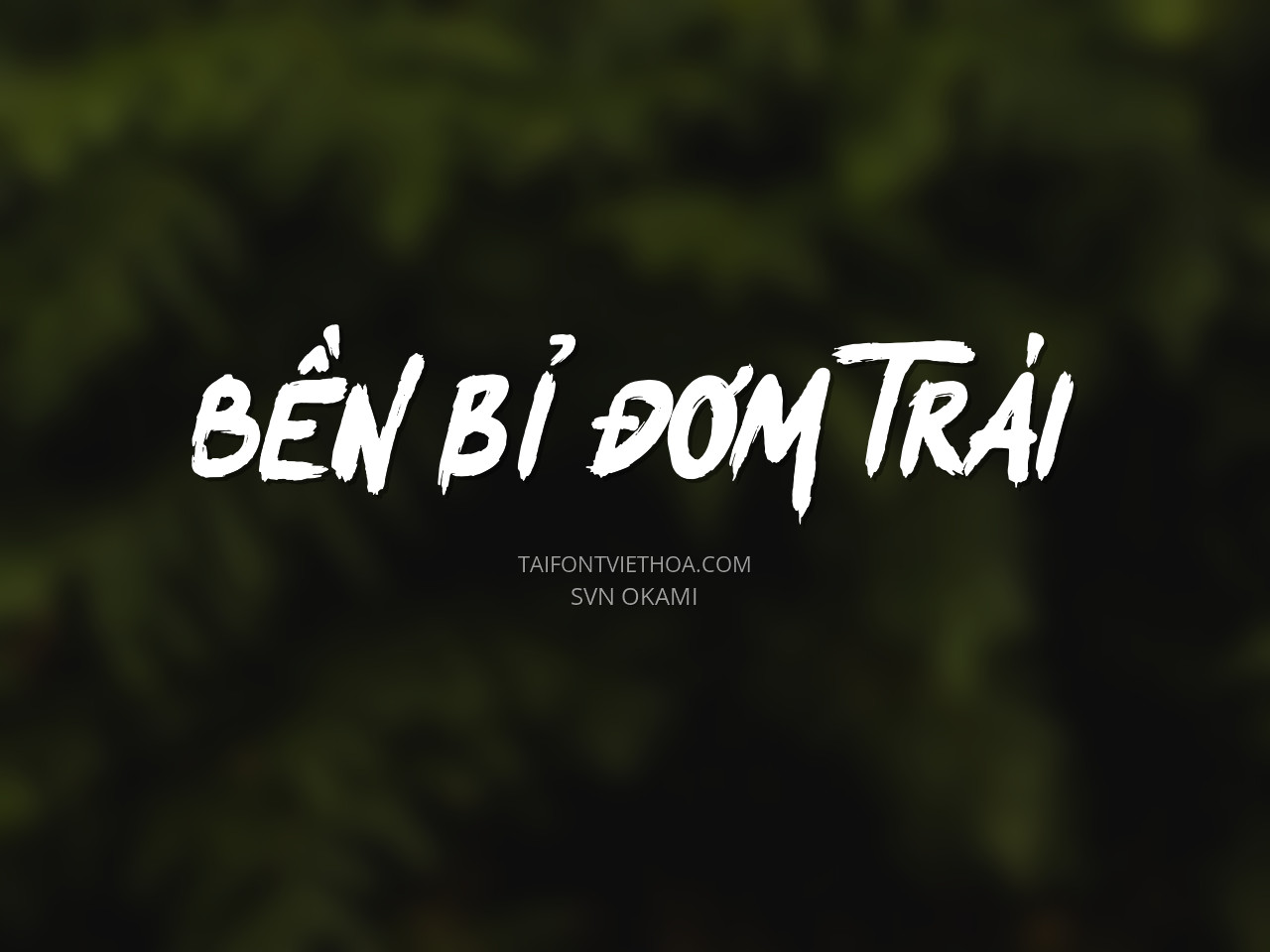
Font việt hóa SVN Okami
Giới thiệu về font SVN Okami – Phong cách chữ viết tay Nhật Bản độc đáo và uyển chuyển
SVN Okami là phiên bản Việt hóa của font Okami – một kiểu chữ lấy cảm hứng từ nét thư pháp Nhật Bản truyền thống, kết hợp giữa sự uyển chuyển và sức mạnh biểu cảm trong từng nét chữ. Font mang đậm phong cách văn hóa Đông Á, đặc biệt là nghệ thuật thư pháp với các đường nét mềm mại nhưng mạnh mẽ, phù hợp cho các dự án thiết kế mang tính nghệ thuật, văn hóa và cá nhân hóa cao.
Phiên bản Việt hóa của SVN Okami được Taifontviethoa.comtuyển chọn và chỉnh sửa, hỗ trợ đầy đủ dấu tiếng Việt cùng hơn 60 ngôn ngữ khác. Font giữ nguyên tinh thần truyền thống của bản gốc, giúp các nhà thiết kế dễ dàng ứng dụng trong các sản phẩm sáng tạo tại Việt Nam, đặc biệt là trong lĩnh vực nghệ thuật, thời trang và văn hóa.
Đường nét thư pháp uyển chuyển – Lý tưởng cho thiết kế nghệ thuật và văn hóa
SVN Okami có thiết kế thư pháp với các nét bút linh hoạt, uyển chuyển, độ nghiêng nhẹ và sự cân bằng hài hòa trong từng ký tự. Font mang lại cảm giác truyền thống, trang nhã nhưng vẫn rất năng động và sáng tạo. Phong cách chữ này rất phù hợp để sử dụng trong thiệp mời, logo, bìa sách, poster nghệ thuật và các dự án đòi hỏi sự tinh tế, cá tính và đậm bản sắc văn hóa.
Ứng dụng lý tưởng: thiết kế nghệ thuật, thư pháp, thiệp cưới, logo thương hiệu cá nhân, sản phẩm thủ công, poster văn hóa, bìa sách và các dự án sáng tạo mang phong cách Á Đông. Ngành nghề phù hợp: nghệ thuật, thiết kế, văn hóa, thời trang, truyền thông sáng tạo và các thương hiệu định vị theo phong cách truyền thống, đậm chất cá nhân.